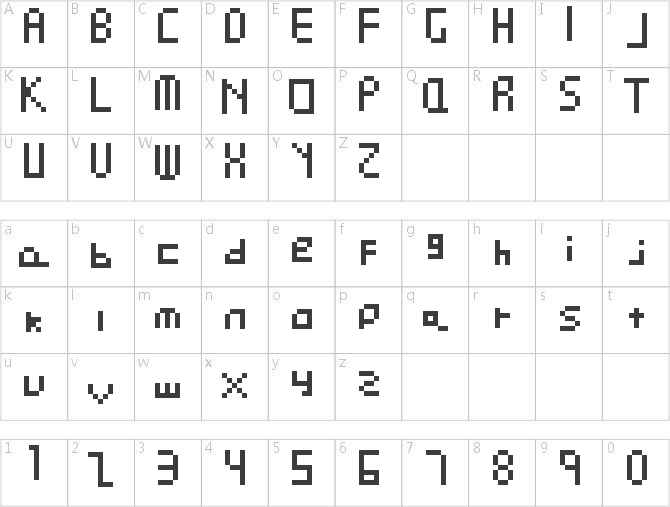
Pixel-Perfect-Regular 詳情頁
字體名稱: Pixel-P
Pixel-Perfect-Regular
Pixel-Perfect-Regular字體字庫是一款讓人賞心悅目、百看不厭的英文字體,適合各類廣告和產品包裝設計應用,字體大小0.01MB,格式為ttf字體,上傳用戶是Honor,作者/版權方為未知